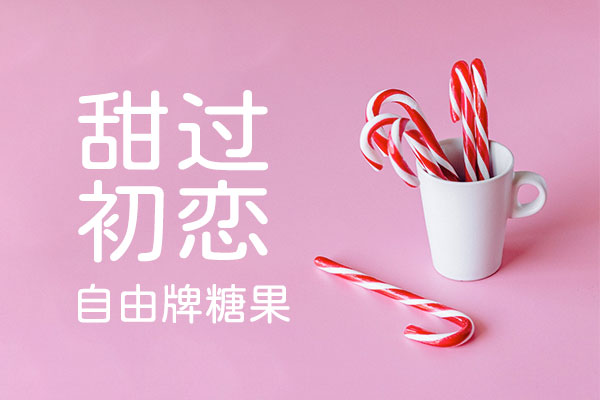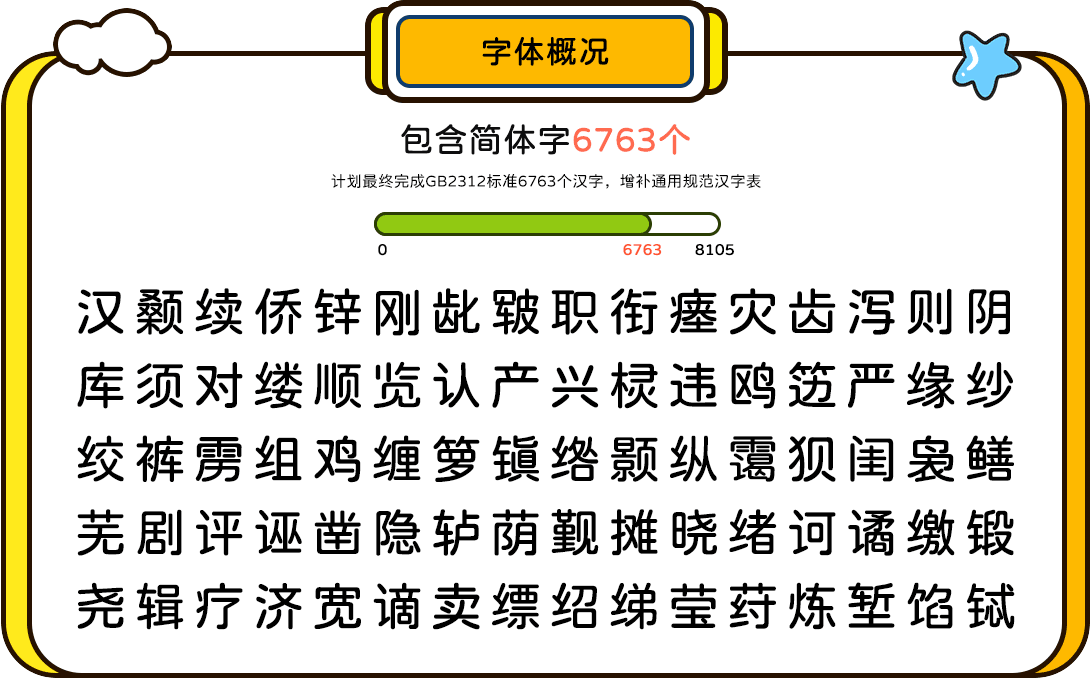
猫啃网糖圆体
猫啃网糖圆体,又名为maoken tangyuan beta,是由猫啃网在免费开源的小杉圆体和jf open粉圆的基础上,经过整合和增补简体字形精心打造而成的一款字体。
到目前为止,猫啃网糖圆体已经包含了简体国标GB2312标准的全部6763个汉字,对于日常使用来说,基本上不存在缺字的现象。未来,猫啃网糖圆体还将继续增补通用规范汉字表,以完善字库。
猫啃网糖圆体效果预览
猫啃网糖圆体字体效果预览